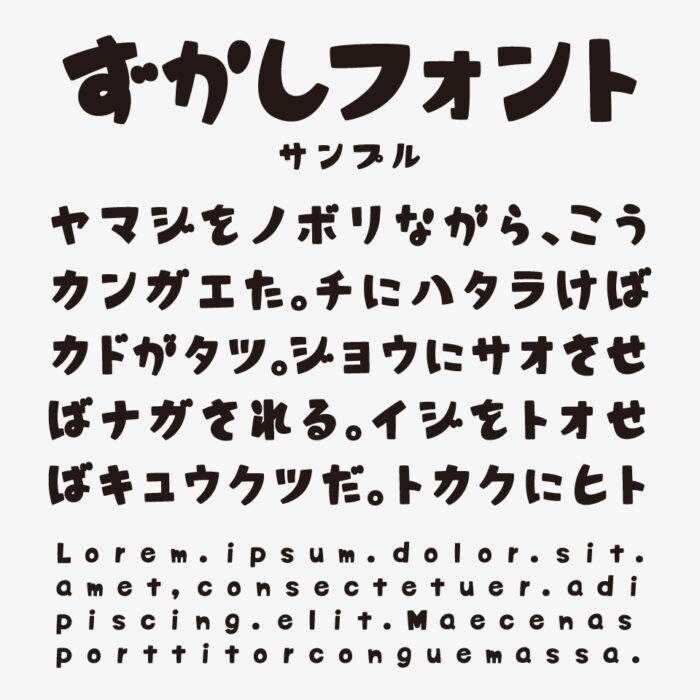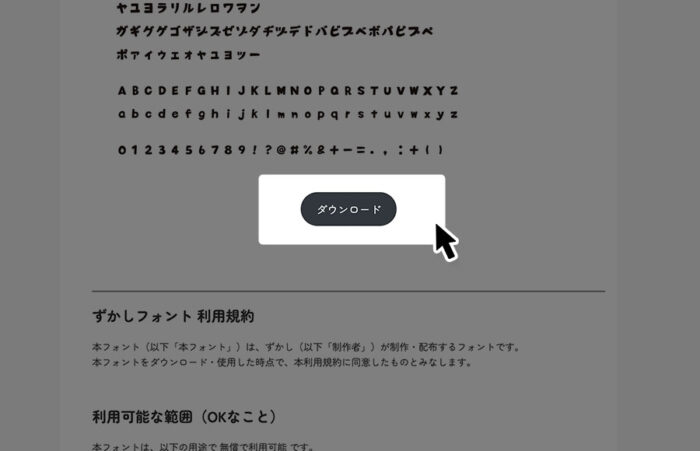
ずかしフォントは、ぽってりとしたウェイトと手書きっぽいさのある個性的文字が魅力の、ポップなデザインフォントです。
文字ごとの太さやサイズ感に揺らぎがあり、どこか愛嬌のある可愛らしい見た目が印象的なフォントです。可愛らしいフォントなのでキッズ向けや絵本やアニメのタイトルロゴなどにぴったりなインパクトあるフォントがあります。
ずかしフォント
収録文字は、ひらがな・カタカナ・アルファベット・数字・記号が収録されています。